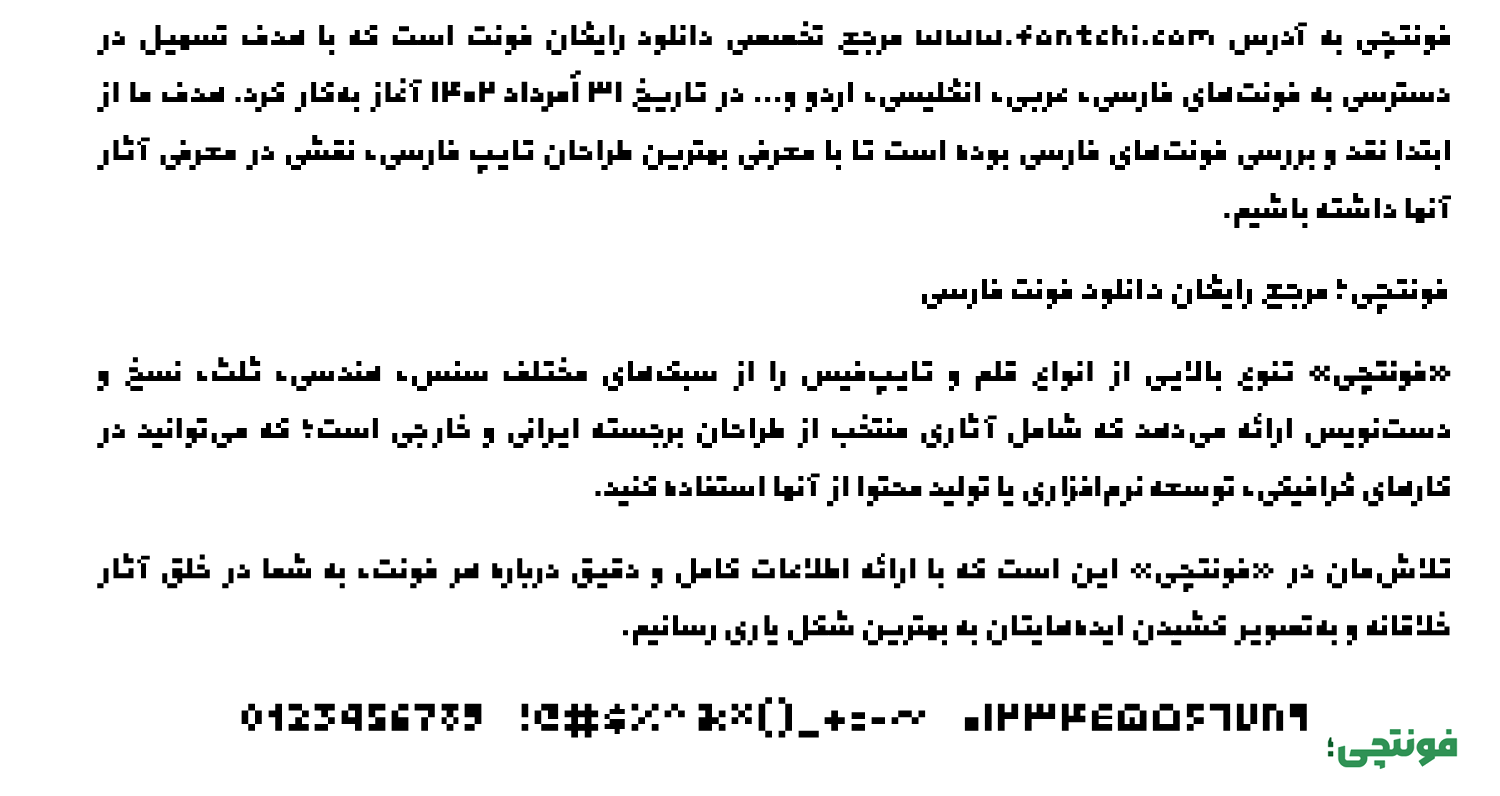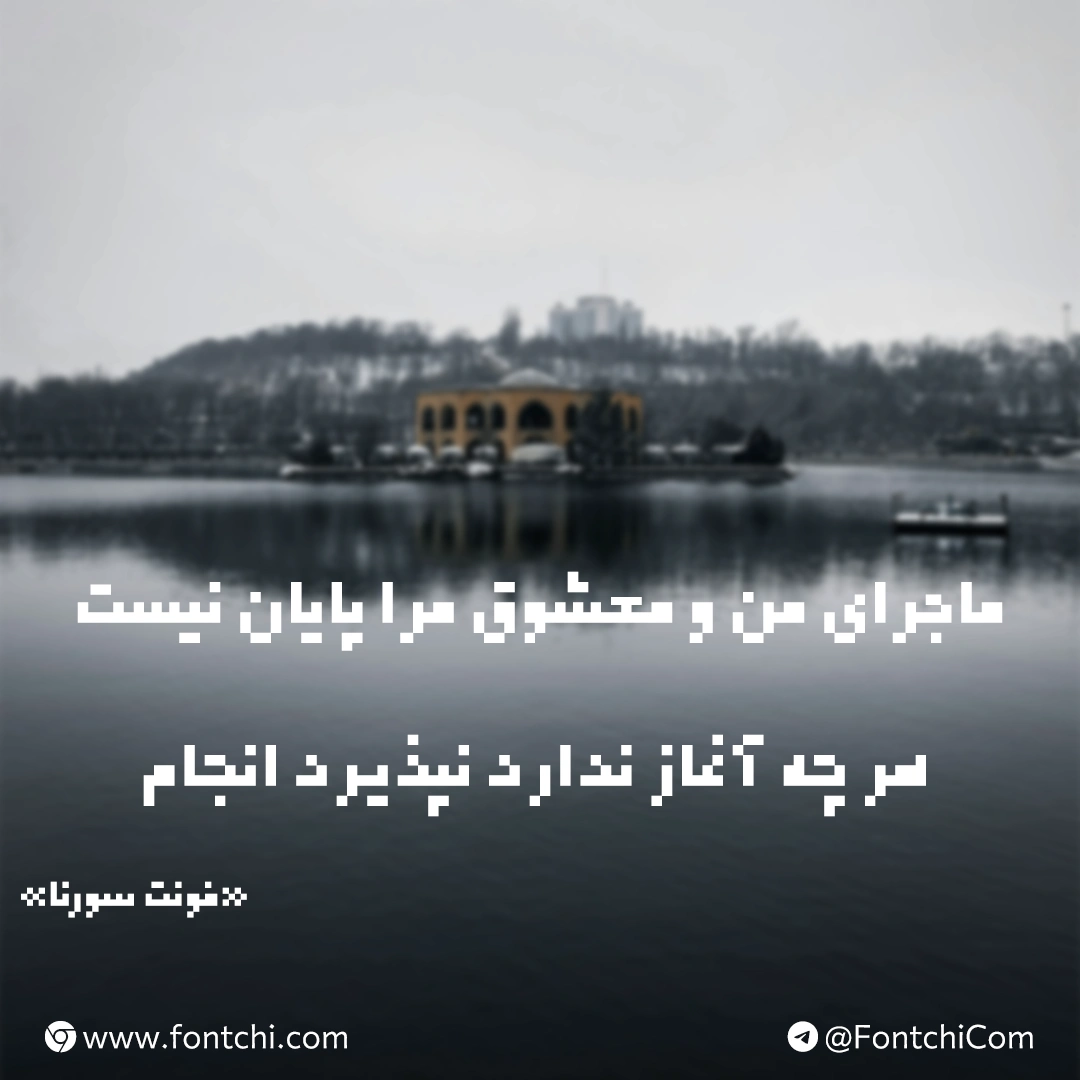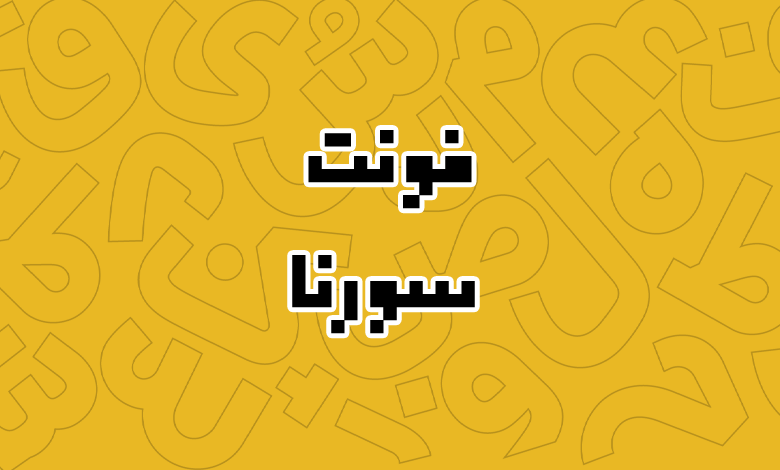
فونت سورنا (Sorena)
فونت سورنا (به انگلیسی: Sorena) از سری فونتهای هندسی آزاد است که به سبک پیکسلی طراحی شده است. از این فونت میتوانید در کارهای خلاقانه و گرافیکی همچون پوسترهای بازی و دنیای تکنولوژی بهترین استفاده را داشته باشید.
فونت رایگان سورنا دارای دو ساختار است. یک ساختار نرمال و طبیعی و دیگری ساختار پیکسلی که ظاهر فانتزیتر و هندسیتری دارد. همچنین این فونت دارای نسخه مخصوص اعداد فارسی هک شده است که در کمتر فونت رایگانی وجود دارد. در ادامه به بررسی بیشتر این فونت میپردازیم.
فونت فارسی سورنا (Sorena) رایگان
این فونت از زبانهای فارسی، عربی و انگلیسی پشتیبانی میکند. ساختار اعراب در همنشینی خوبی با سایر حروف قرار دارند. در این فونت پیکسلی که نمونه آن را در فونت رویین مشاهده کردهایم، حروف با ظرافت خاصی با رعایت طراحی فرم هندسی در حروف ساخته شدهاند تا ظاهر فونت در همه بخشها منسجم باشد.
از فونت سورنا رایگان میتوانید استفادههای مختلفی داشته باشید. این فونت که از اولین ساختههای محمد درویشی است، سبب شکلگیری فونت حرفهایتر با وزنهای بیشتر به نام رویین شد. از جمله کاربردهای این فونت میتوان به موارد زیر اشاره کرد:
- طراحی پوسترهای خلاقانه و گرافیکی مرتبط با بازی.
- استفاده در شبکههای اجتماعی و تامنیل ویدئوهای یوتوب.
- استفاده در مطبوعات و چاپ بنرهای مرتبط با رویدادهای تکنولوژی.